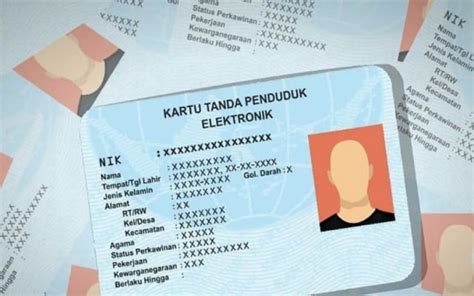
Font KTP Elektronik: Pilihan Terbaik
Guys, pernah nggak sih kalian kepo sama jenis font yang dipakai di KTP elektronik kita? Pasti sering dong ya ngeliatin KTP sendiri atau KTP teman, terus mikir, “Kok tulisannya gitu amat ya?” Nah, di artikel kali ini, kita bakal kupas tuntas soal font KTP elektronik, mulai dari kenapa pakai font itu, ada pilihan font lain nggak, sampai gimana sih font itu bisa bikin KTP kita kelihatan lebih resmi dan profesional. Siap-siap ya, kita bakal menyelami dunia font yang mungkin selama ini luput dari perhatian kalian.
Mengapa Font Tertentu Dipilih untuk KTP Elektronik?
Jadi gini, guys, pemilihan font untuk dokumen resmi kayak KTP elektronik itu nggak sembarangan lho. Ada banyak banget pertimbangan di baliknya, dan salah satunya yang paling penting adalah keterbacaan atau readability . Bayangin aja kalau font-nya kecil, nyeleneh, atau susah dibaca, gimana nanti petugas pas ngecek data kalian? Atau malah pas kalian sendiri yang lagi buru-buru mau nunjukkin KTP, eh malah bingung bacanya. Makanya, pemerintah biasanya memilih font yang jelas , bersih , dan mudah dibaca dalam berbagai ukuran. Selain itu, font yang dipilih juga harus punya karakter yang kuat dan terlihat profesional serta resmi . Nggak mungkin dong ya, KTP negara kita pakai font yang kelihatan kekinian banget kayak font Comic Sans atau font yang bentuknya meliuk-liuk kayak tulisan tangan. Tujuannya adalah untuk memberikan kesan otoritas dan kepercayaan pada dokumen tersebut. Font yang tepat juga bisa bantu mencegah pemalsuan lho, karena font-font tertentu punya karakteristik yang sulit ditiru. Jadi, font yang ada di KTP elektronik itu sebenarnya hasil dari riset dan pertimbangan matang demi kenyamanan dan keamanan kita semua. Nggak heran kan kalau seringkali font yang dipakai itu cenderung serif atau sans-serif yang klasik dan nggak lekang oleh waktu. Font-font ini udah terbukti secara historis bisa tampil baik di berbagai media cetak maupun digital, sehingga cocok banget buat identitas negara yang harus awet dan terpercaya. Selain itu, keseragaman font di seluruh Indonesia juga penting banget, guys. Biar nggak ada kebingungan atau perbedaan persepsi soal tampilan KTP antar daerah. Jadi, ya, pilihan font di KTP elektronik itu punya alasan kuat di baliknya, bukan cuma asal pilih lho!
Apa Saja Jenis Font yang Umum Digunakan di Dokumen Resmi?
Nah, ngomongin font untuk dokumen resmi, ada beberapa jenis font yang sering banget jadi pilihan utama para desainer grafis dan institusi. Yang paling populer itu biasanya adalah font sans-serif dan serif . Kalau sans-serif itu kan yang nggak punya ‘kaki’ di ujung hurufnya, kayak Arial, Helvetica, atau Calibri. Font jenis ini kesannya lebih modern, bersih, dan gampang dibaca di layar komputer atau layar digital lainnya. Makanya, banyak banget aplikasi, website, atau bahkan KTP elektronik kita pakai font jenis ini. Mereka itu terlihat simpel tapi elegan, guys. Nggak banyak embel-embel yang bikin pusing. Cocok banget buat nyampein informasi yang padat dan jelas. Di sisi lain, ada juga font serif . Ciri khasnya itu punya ‘kaki’ atau garis kecil di ujung hurufnya, contohnya Times New Roman, Georgia, atau Garamond. Font serif ini biasanya kesannya lebih tradisional, klasik, dan berwibawa. Cocok banget buat buku, koran, atau dokumen-dokumen yang butuh kesan formal dan intelektual . Makanya, meskipun KTP elektronik banyak pakai sans-serif, kadang ada juga dokumen resmi lain yang masih pakai serif untuk memberikan kesan yang berbeda. Selain kedua jenis utama ini, ada juga font slab serif , yang ‘kakinya’ lebih tebal dan kotak, atau font script yang meniru tulisan tangan (tapi ini jarang banget dipakai di dokumen resmi karena sulit dibaca). Intinya, untuk dokumen resmi, pilihan font itu mengerucut ke font yang jelas , terstruktur , dan mudah dikenali . Nggak ada ruang buat font yang aneh-aneh atau sulit diinterpretasikan. Kestabilan dan keterbacaan adalah kunci utama, guys. Jadi, kalau kalian perhatikan font di KTP, paspor, ijazah, atau surat-surat penting lainnya, kemungkinan besar kalian akan menemukan salah satu dari jenis font klasik ini. Mereka itu udah teruji zaman dan terbukti efektif dalam menyampaikan informasi secara profesional. Jadi, bukan cuma soal estetika, tapi juga soal fungsionalitas dan citra institusi yang diwakili oleh dokumen tersebut. Keren kan, sebuah font bisa punya ‘tanggung jawab’ sebesar itu!
Font KTP Elektronik: Apakah Ada Pilihan Lain?
Nah, ini nih yang sering bikin penasaran. Kalau font yang dipakai di KTP elektronik itu udah ada, apakah kita bisa milih font lain? Jawabannya, sayangnya tidak . Font yang digunakan di KTP elektronik itu sudah ditentukan oleh standar pemerintah. Jadi, setiap KTP elektronik yang diterbitkan di Indonesia akan menggunakan font yang sama untuk memastikan keseragaman dan profesionalisme . Kenapa sih nggak bisa milih? Gini, guys, KTP itu kan bukan kayak postingan Instagram yang bisa kita utak-atik font-nya sesuka hati. KTP adalah dokumen identitas resmi negara yang harus punya standar yang sama di seluruh wilayah. Kalau setiap orang bisa pilih font sendiri, bayangin aja nanti KTP-nya bakal berantakan, nggak seragam, dan malah mengurangi kredibilitasnya sebagai dokumen resmi. Selain itu, pemilihan font itu juga melibatkan pertimbangan teknis, seperti bagaimana font tersebut akan tercetak di berbagai jenis printer, bagaimana tampilannya saat discan, dan bagaimana data digitalnya tersimpan. Jadi, ya, kita memang tidak punya pilihan untuk font di KTP elektronik kita. Kita harus menerima font yang sudah ditetapkan. Tapi jangan khawatir, guys! Font yang dipilih itu biasanya adalah font yang sudah teruji dan memang bagus untuk dibaca. Jadi, meskipun nggak bisa milih, kualitas tampilannya tetap terjamin kok. Fokus utama pemerintah adalah memastikan bahwa KTP kalian itu jelas , mudah dibaca , dan terlihat resmi . Jadi, meskipun kita nggak bisa request font favorit kita, kita bisa bangga karena KTP kita punya tampilan yang seragam, profesional, dan sesuai standar internasional untuk dokumen identitas. Anggap aja font itu adalah ‘seragam’ KTP kita, yang bikin semua KTP terlihat sama di mata negara. Penting banget kan keseragaman ini demi tertib administrasi kependudukan. Jadi, terima saja font yang ada, karena di balik itu ada banyak pertimbangan demi kebaikan bersama. Dan jujur aja, font yang dipakai di KTP itu udah cukup baik dan fungsional kok buat sebuah dokumen penting.
Memahami Keterbacaan dan Kejelasan Font
Keterbacaan dan kejelasan font itu ibaratnya kayak seberapa gampang kita ngerti omongan orang. Kalau ngomongnya jelas, terstruktur, dan pakai intonasi yang pas, kan kita gampang nangkap pesannya. Nah, font juga gitu, guys. Di KTP elektronik, keterbacaan itu nomor satu. Kenapa? Karena KTP itu kan isinya data penting: nama, tanggal lahir, alamat, nomor NIK, dan lain-lain. Data ini harus bisa dibaca sekilas tanpa bikin mata kita juling atau kepala pusing. Font yang dipilih pasti punya karakter yang tegas tapi tidak berlebihan . Huruf-hurufnya jelas bentuknya, nggak saling nyambung aneh-aneh, dan jarak antar hurufnya juga pas. Coba deh perhatiin font di KTP kalian. Kebanyakan pasti font sans-serif yang bersih, kan? Kayak Arial atau sejenisnya. Font jenis ini memang didesain supaya gampang dibaca di berbagai ukuran, dari yang kecil sampai yang agak besar. Nggak ada ‘hiasan’ yang nggak perlu yang bisa bikin bingung. Selain itu, ada juga yang namanya kejelasan atau clarity . Ini tuh maksudnya gimana font itu bisa membedakan satu huruf dengan huruf lainnya dengan mudah. Misalnya, bedanya huruf ‘i’ kecil sama ‘l’ kecil, atau huruf ‘o’ sama angka ‘0’. Font yang buruk bisa bikin huruf-huruf ini kelihatan sama, nah ini bahaya banget buat dokumen resmi. Makanya, font di KTP itu pasti didesain biar perbedaan antar karakter itu kentara . Bayangin aja kalau di KTP tertulis ‘10rn’ padahal harusnya ‘10rn’. Wah, bisa bikin masalah besar! Jadi, pemilihan font itu nggak cuma soal gaya, tapi soal fungsi . Fungsi utamanya adalah menyampaikan informasi dengan akurat dan cepat . Keterbacaan dan kejelasan ini juga penting banget buat KTP elektronik yang datanya tersimpan secara digital. Font yang jelas akan memudahkan saat proses scanning atau saat data ditampilkan di layar. Jadi, nggak heran kalau font yang dipakai itu cenderung yang klasik dan teruji . Mereka udah membuktikan diri bisa tampil baik dalam menyampaikan informasi penting tanpa menimbulkan keraguan. So, lain kali kalau kalian lihat KTP, coba deh perhatiin gimana fontnya didesain dengan baik untuk memastikan semua data terbaca dengan sempurna. Itu adalah bukti kecermatan dalam desain dokumen negara, guys!
Font KTP Elektronik dan Kesan Profesionalisme
Guys, pernah kepikiran nggak sih kenapa dokumen resmi kayak KTP itu harus kelihatan profesional ? Salah satunya ya karena font yang digunakan. Pemilihan font itu punya peran besar lho dalam membentuk persepsi orang terhadap sebuah dokumen. Kalau font-nya terlihat rapi, jelas, dan punya ‘wibawa’, otomatis dokumen itu jadi kelihatan lebih resmi dan terpercaya . Nah, di KTP elektronik, font yang dipilih biasanya itu adalah font yang punya kesan serius dan elegan . Nggak ada font yang terlalu ‘gaul’, terlalu banyak hiasan, atau terkesan main-main. Kenapa? Karena KTP itu adalah identitas resmi kalian sebagai warga negara. Bayangin aja kalau KTP kalian pakai font yang aneh, kayak font ala-ala tulisan tangan yang sulit dibaca, atau font yang terlalu tebal dan mencolok kayak buat spanduk diskon. Pasti nggak banget, kan? Kesannya jadi nggak profesional dan malah mengurangi kepercayaan orang terhadap dokumen tersebut. Font yang digunakan di KTP biasanya adalah jenis font sans-serif yang clean dan modern, atau kadang ada juga yang pakai font serif klasik yang memberikan kesan tradisional dan berwibawa . Apapun jenisnya, yang pasti font itu dipilih karena memiliki karakteristik yang kuat dan mudah dibaca . Keterbacaan yang baik ini sendiri sudah menjadi bagian dari profesionalisme. Dokumen yang mudah dibaca menunjukkan bahwa pembuatnya menghargai pembacanya dan ingin menyampaikan informasi dengan efektif. Selain itu, keseragaman font di seluruh KTP juga memberikan kesan profesionalisme yang sama untuk semua warga negara. Ini menunjukkan bahwa negara memperlakukan semua warganya dengan standar yang sama dalam hal identitas resmi. Jadi, font di KTP itu bukan cuma sekadar ‘tulisan’, tapi dia adalah bagian dari branding negara yang merepresentasikan otoritas dan kepercayaan . Dengan menggunakan font yang tepat, KTP elektronik kita jadi terlihat lebih solid , berkelas , dan tentunya sangat profesional . Ini penting banget untuk menjaga citra dokumen negara di mata publik, baik di dalam maupun luar negeri. So, meskipun kita nggak bisa milih fontnya, kita patut mengapresiasi pilihan font yang ada karena sudah berkontribusi besar dalam menciptakan citra KTP yang profesional dan terpercaya. Keren kan, sebuah font bisa punya ‘kekuatan’ sebesar itu untuk sebuah dokumen penting!,
Kesimpulan: Pentingnya Font dalam Dokumen Identitas
Jadi, guys, setelah kita ngobrolin panjang lebar soal font KTP elektronik, kita bisa tarik kesimpulan nih kalau font itu punya peran yang sangat penting , terutama dalam dokumen identitas seperti KTP. Ini bukan cuma soal gaya-gayaan, tapi lebih ke arah fungsionalitas , kejelasan , dan profesionalisme . Font yang dipilih untuk KTP elektronik itu bukan sembarangan. Ada pertimbangan matang di baliknya, mulai dari keterbacaan yang maksimal biar data penting bisa dibaca dengan cepat dan akurat, sampai ke kesan profesional dan resmi yang harus terpancar dari dokumen identitas negara. Keterbacaan itu kunci utamanya, bayangin aja kalau fontnya susah dibaca, bisa repot kan urusannya pas lagi perlu nunjukkin KTP. Terus, kesan profesional itu penting banget buat KTP sebagai representasi diri kalian di mata hukum dan masyarakat. Font yang clean, jelas, dan terstruktur bikin KTP terlihat lebih berwibawa dan terpercaya. Meskipun kita sebagai pengguna nggak bisa milih font kesukaan kita di KTP, kita harus paham bahwa ini demi keseragaman dan standarisasi yang baik. Kalau semua orang bisa milih font sendiri, bayangin aja KTP bakal jadi kayak pasar malam, nggak seragam dan malah mengurangi kredibilitasnya. Jadi, font yang ada di KTP itu sebenarnya sudah hasil pilihan terbaik yang memenuhi kriteria teknis dan estetika untuk sebuah dokumen penting. Penting banget untuk diingat bahwa setiap elemen dalam sebuah dokumen identitas itu punya fungsi dan tujuannya masing-masing, termasuk font. Jadi, meskipun terlihat sepele, font itu berkontribusi besar dalam memastikan KTP kita valid , terpercaya , dan mudah digunakan . Oleh karena itu, mari kita hargai pilihan font yang ada di KTP elektronik kita, karena di baliknya ada upaya untuk memastikan dokumen penting kita ini tampil optimal dan profesional . Keren kan, sebuah pilihan font bisa punya dampak sebesar itu pada sebuah dokumen identitas negara!